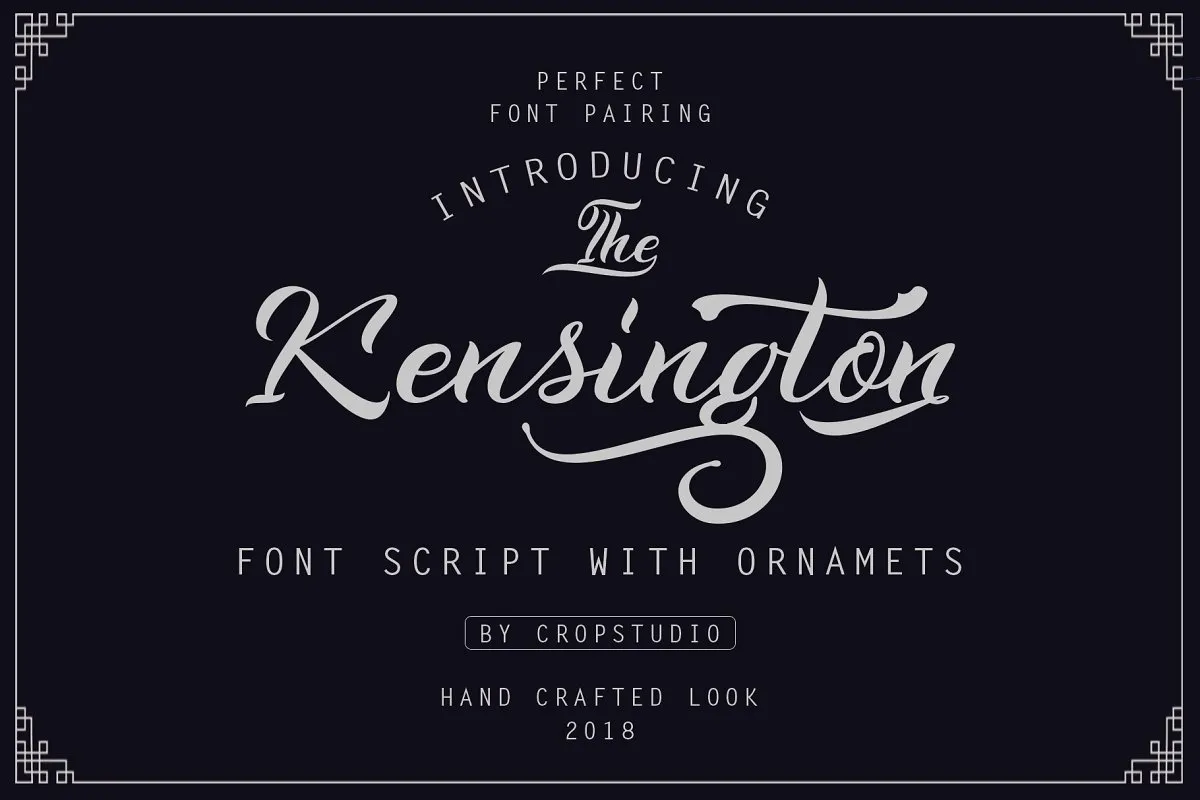
Kensington Calligraphy Font – Download Grátis
Descubra a Kensington Calligraphy Font, uma opção única para designers que buscam dar um toque autêntico às suas criações digitais. Esta fontes Script é ideal para adicionar um ar de arte manual aos seus projetos gráficos. Inspirada na sensação do design retrô, Kensington oferece um charme moderno e elegante. Perfeita tanto para t-shirts como para signagens, logos e cabeçalhos, esta fonte atinge perfeitamente o estilo desejado em qualquer aplicação visual. Seja ela um toque de personalidade nos seus estímulos visuais ou uma forma refinada de expressar seu conceito design em identidades corporativas, Kensington é a escolha ideal para designers e criadores de conteúdo que buscam trazer um aspecto retrô à suas criações digitais.